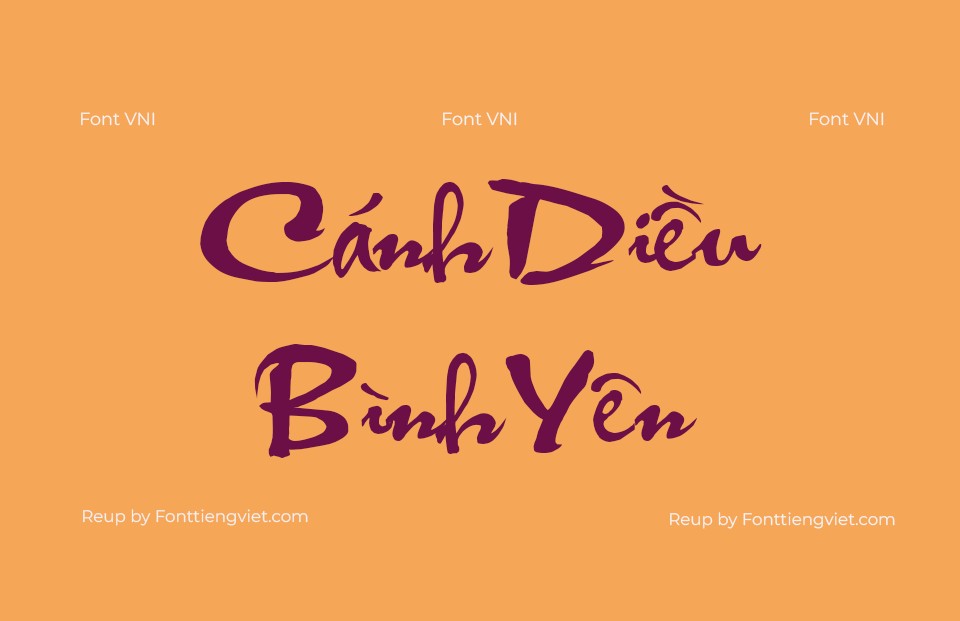
Trong thế giới thiết kế đồ họa, việc tìm kiếm một Font Chữ độc đáo và đậm chất văn hóa Việt Nam luôn là ưu tiên hàng đầu. Một trong những lựa chọn kinh điển không thể bỏ qua chính là Font Việt hoá VNI Thuphap2. Đây không chỉ là một phông chữ; nó là sự kết hợp tinh tế giữa nghệ thuật thư pháp truyền thống và khả năng ứng dụng hiện đại. Nó mang đến nét đẹp mềm mại, uyển chuyển, rất phù hợp cho các ấn phẩm cần sự trang trọng và tính nghệ thuật cao. Phông chữ này đã được Việt hóa hoàn chỉnh, đảm bảo hiển thị đầy đủ và chính xác các dấu tiếng Việt, giải quyết triệt để vấn đề lỗi font thường gặp.
Sức Hút Khó Cưỡng Của Font Việt hoá VNI Thuphap2 Trong Thiết Kế
Font thư pháp từ lâu đã chiếm một vị trí đặc biệt trong lòng người Việt Nam. Nó gợi lên hình ảnh về những nét chữ ông đồ, những câu đối Tết, hay những bức thư pháp ý nghĩa. Font Việt hoá VNI Thuphap2 kế thừa tinh hoa đó, mang lại một bộ ký tự phong phú với độ thẩm mỹ cao. Điểm mạnh lớn nhất của font này là sự cân bằng hoàn hảo giữa tính cổ điển và tính dễ đọc. Dù là trong các dự án in ấn lớn hay các thiết kế web hiện đại, phông chữ này vẫn giữ được vẻ trang trọng mà không làm mất đi sự thân thiện với người đọc. Sự uyển chuyển trong từng nét chữ, từ nét thanh đến nét đậm, tạo nên một cảm giác tự nhiên, như thể được viết bằng bút lông thật. Đối với các nhà thiết kế đang tìm kiếm một “chữ ký” văn hóa cho tác phẩm của mình, VNI Thuphap2 là một công cụ không thể thiếu.
Đặc Điểm Kỹ Thuật và Quy Trình Việt Hóa Hoàn Chỉnh
Dòng font VNI Thuphap2 ban đầu được phát triển theo bộ mã VNI, một hệ thống mã hóa đã từng rất phổ biến tại Việt Nam. Tuy nhiên, việc sử dụng các font chưa Việt hóa hoặc chỉ Việt hóa sơ sài thường gây ra phiền toái lớn, đặc biệt là khi làm việc với các phần mềm đồ họa chuyên nghiệp như Adobe Photoshop hay Illustrator. Phiên bản Font Việt hoá VNI Thuphap2 đã được tối ưu hóa để tương thích rộng rãi hơn, thường được đóng gói dưới dạng font Unicode hoặc có các tùy chọn chuyển đổi dễ dàng, giúp người dùng thoải mái sử dụng trên mọi hệ điều hành từ Windows đến macOS mà không gặp rắc rối về hiển thị. Quá trình Việt hóa không chỉ đơn thuần là thêm dấu, mà còn phải điều chỉnh kerning (khoảng cách giữa các ký tự) và hinting để đảm bảo chất lượng hiển thị sắc nét nhất ở mọi kích thước. Điều này đặc biệt quan trọng đối với học sinh và giáo viên khi soạn thảo tài liệu ôn thi tốt nghiệp, nơi sự rõ ràng và chính xác là tối quan trọng.
Việc sử dụng font thư pháp trong môi trường giáo dục, đặc biệt là cấp trung học phổ thông, có thể giúp tăng tính thẩm mỹ cho các dự án nhóm, bài thuyết trình, hoặc thậm chí là bìa sách giáo khoa. Nó khuyến khích sự sáng tạo và tôn vinh nét chữ Việt. Nhiều bạn học sinh đã bắt đầu làm quen với typography qua các font như VNI Thuphap2, biến những bài tập khô khan thành những tác phẩm nghệ thuật nhỏ. Đây là một bước đệm quan trọng giúp các em làm quen với ngành thiết kế đồ họa sau này.
Ứng Dụng Đa Dạng Của Phông Chữ VNI Thuphap2
Khả năng ứng dụng của phông chữ này là vô cùng rộng lớn. Đầu tiên phải kể đến là ngành thiết kế thiệp mời, đặc biệt là thiệp cưới hoặc thiệp chúc mừng năm mới. Sự trang nhã và truyền thống của font giúp nâng tầm giá trị của tấm thiệp. Thứ hai, trong lĩnh vực quảng cáo và thương hiệu, các doanh nghiệp thường dùng font thư pháp này để tạo logo hoặc slogan cho các sản phẩm mang đậm chất truyền thống Việt Nam, như trà, cà phê hoặc các sản phẩm thủ công mỹ nghệ. Phông chữ này cũng rất được ưa chuộng trong việc thiết kế bằng khen, chứng chỉ tốt nghiệp, hoặc các văn bằng danh dự, nơi sự trang trọng là yếu tố hàng đầu.
Đối với các nội dung số, VNI Thuphap2 cũng chứng minh được giá trị của mình. Nhiều nhà phát triển nội dung, đặc biệt là những người làm về giáo dục lịch sử và văn hóa, sử dụng font này để tạo điểm nhấn cho các tiêu đề video hoặc infographic. Sự kết hợp giữa kiểu chữ viết tay mềm mại và khả năng hiển thị tiếng Việt hoàn hảo tạo nên sự khác biệt rõ rệt so với các phông chữ Latin thông thường. Điều này giúp thu hút sự chú ý của người xem, đặc biệt là giới trẻ và học sinh, những người luôn tìm kiếm sự mới mẻ trong các tài liệu học tập.
Để tận dụng tối đa vẻ đẹp của phông chữ này, người dùng nên lưu ý đến việc lựa chọn kích cỡ và màu sắc phù hợp. Font thư pháp thường đẹp nhất khi được đặt trên nền trơn hoặc nền có hoa văn nhẹ nhàng, tránh bị rối mắt. Việc kết hợp với một font sans-serif đơn giản cho phần nội dung chính sẽ tạo nên sự hài hòa tuyệt đối, làm nổi bật phần tiêu đề được viết bằng VNI Thuphap2.
Tóm lại, Font Việt hoá VNI Thuphap2 là một tài sản quý giá cho bất kỳ ai hoạt động trong lĩnh vực thiết kế hoặc đơn giản là yêu thích nét đẹp của nghệ thuật thư pháp Việt. Phiên bản Việt hoá hoàn chỉnh không chỉ giải quyết vấn đề kỹ thuật mà còn mở ra vô số cơ hội sáng tạo mới. Nó giúp các nhà thiết kế, giáo viên, và cả các bạn học sinh dễ dàng tạo ra những sản phẩm chất lượng cao, mang đậm bản sắc văn hóa. Nếu bạn đang tìm kiếm một Font Chữ để thêm sự tinh tế và truyền thống vào dự án tiếp theo của mình, VNI Thuphap2 chắc chắn là cái tên đứng đầu danh sách. Hãy tải về và trải nghiệm ngay hôm nay để thấy được sự khác biệt mà tuyệt tác thư pháp này mang lại!